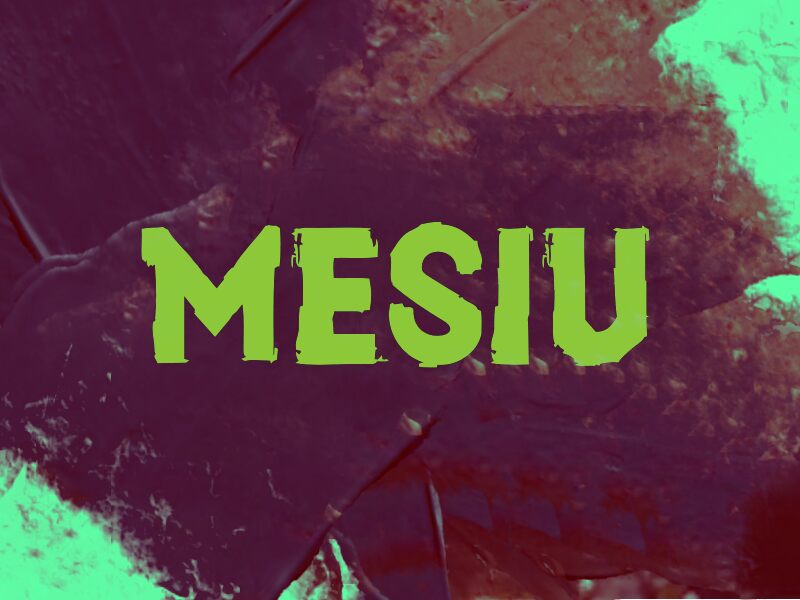
MESIU
MESIU od Wep je bezplatný font typu display so zámerne opotrebovaným vzhľadom, definovaný výraznými, blokovými siluetami a potrhanými vertikálnymi hranami. Písmená vyzerajú, akoby boli vyrezané zo starého, otlčeného nápisu. Drsnosť je konzistentná a nie náhodná – dizajn si zachováva pevnú čiernu hmotu, zatiaľ čo vyštípané medzery a ošúchané rohy mu dodávajú autentický, spracovaný povrch.
Táto textúra vynikne na nadpisoch plagátov, obaloch albumov, letákoch na akcie, hernej grafike či odvážnych headlajnoch na sociálnych sieťach, kde by čistejší font pôsobil príliš neutrálne. Skvele ukotví aj obaly produktov alebo merchandising, ktoré vyžadujú surový, ručne opracovaný vzhľad, pretože poškodenie je súčasťou samotnej štruktúry, nie len pridaným efektom.